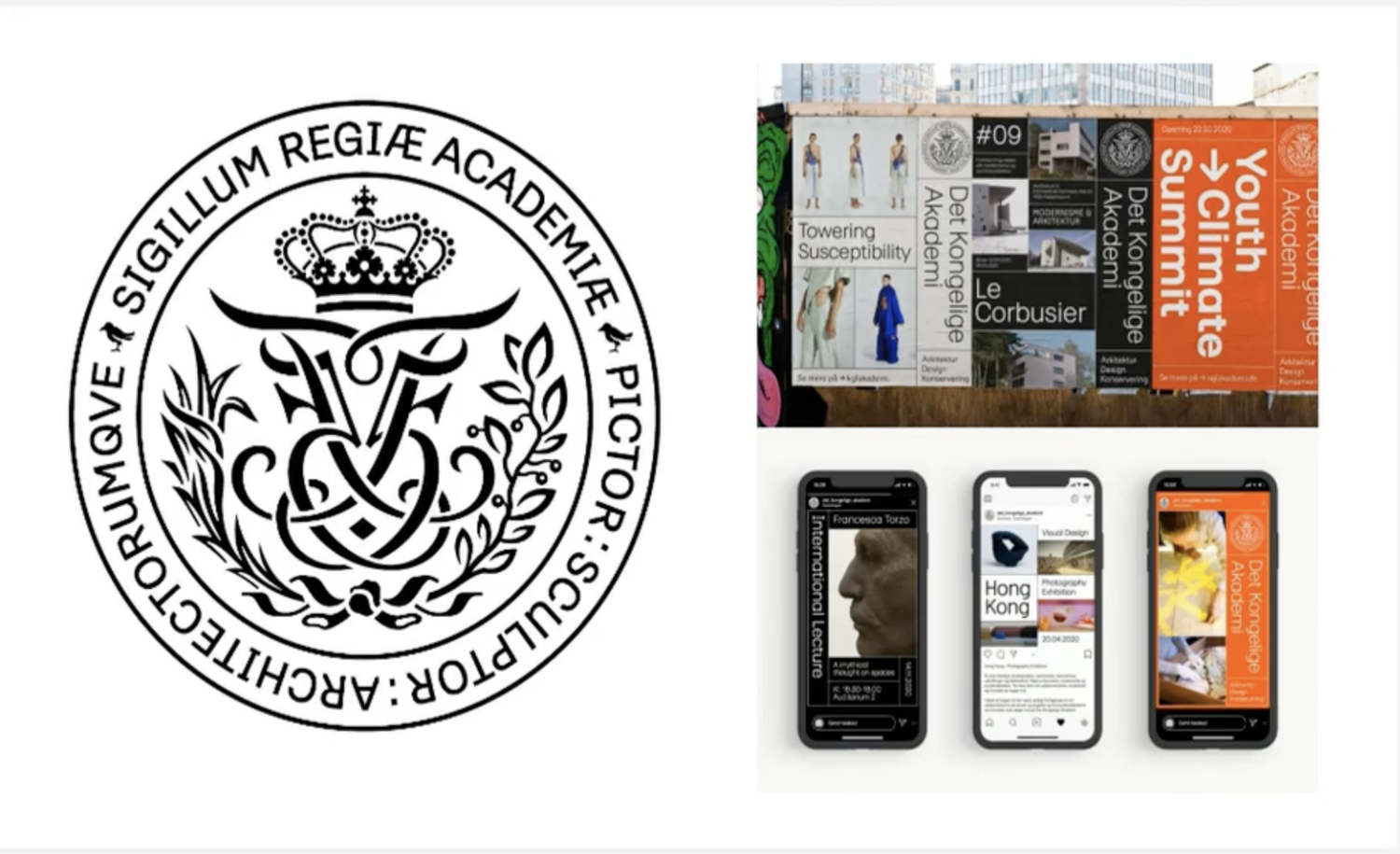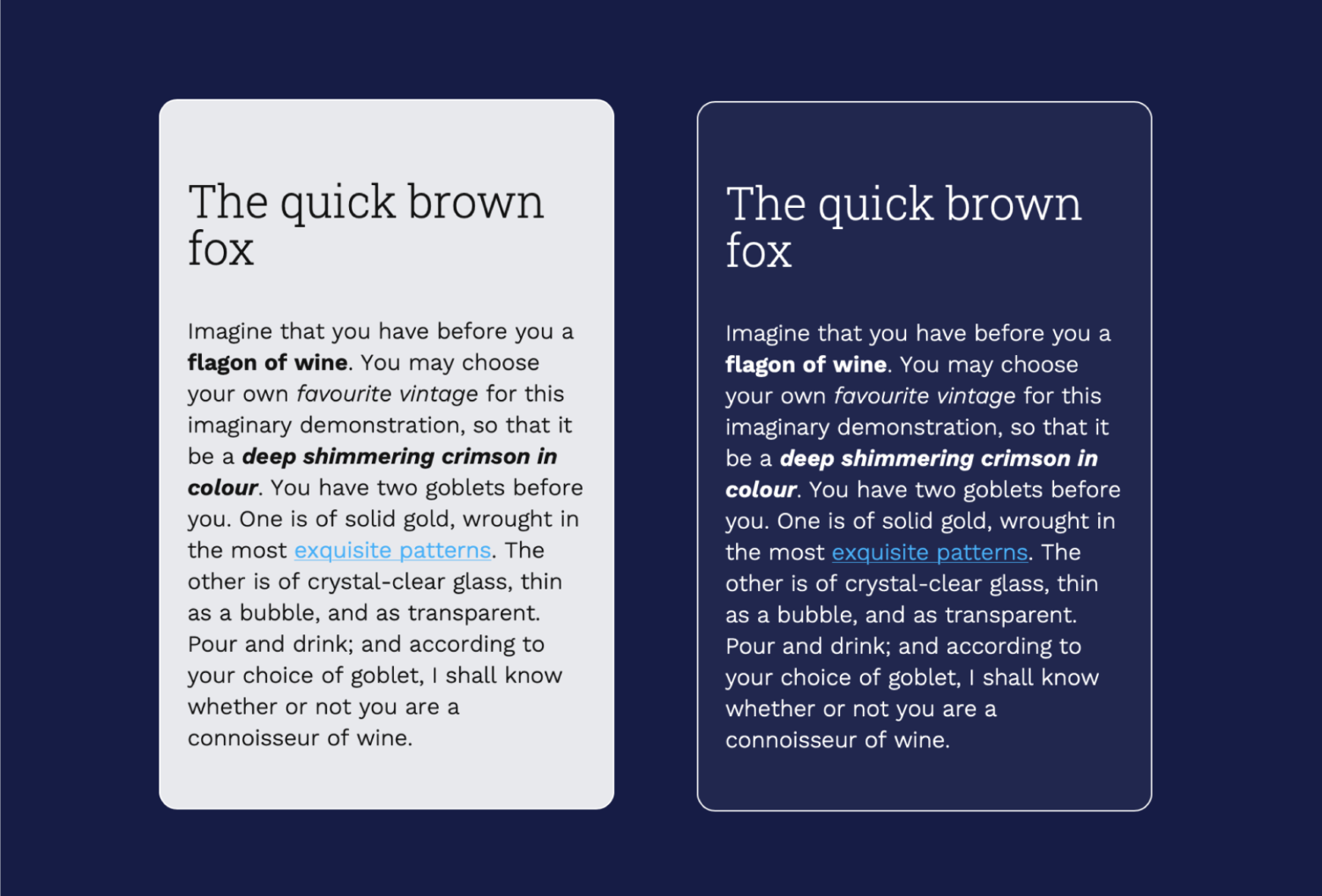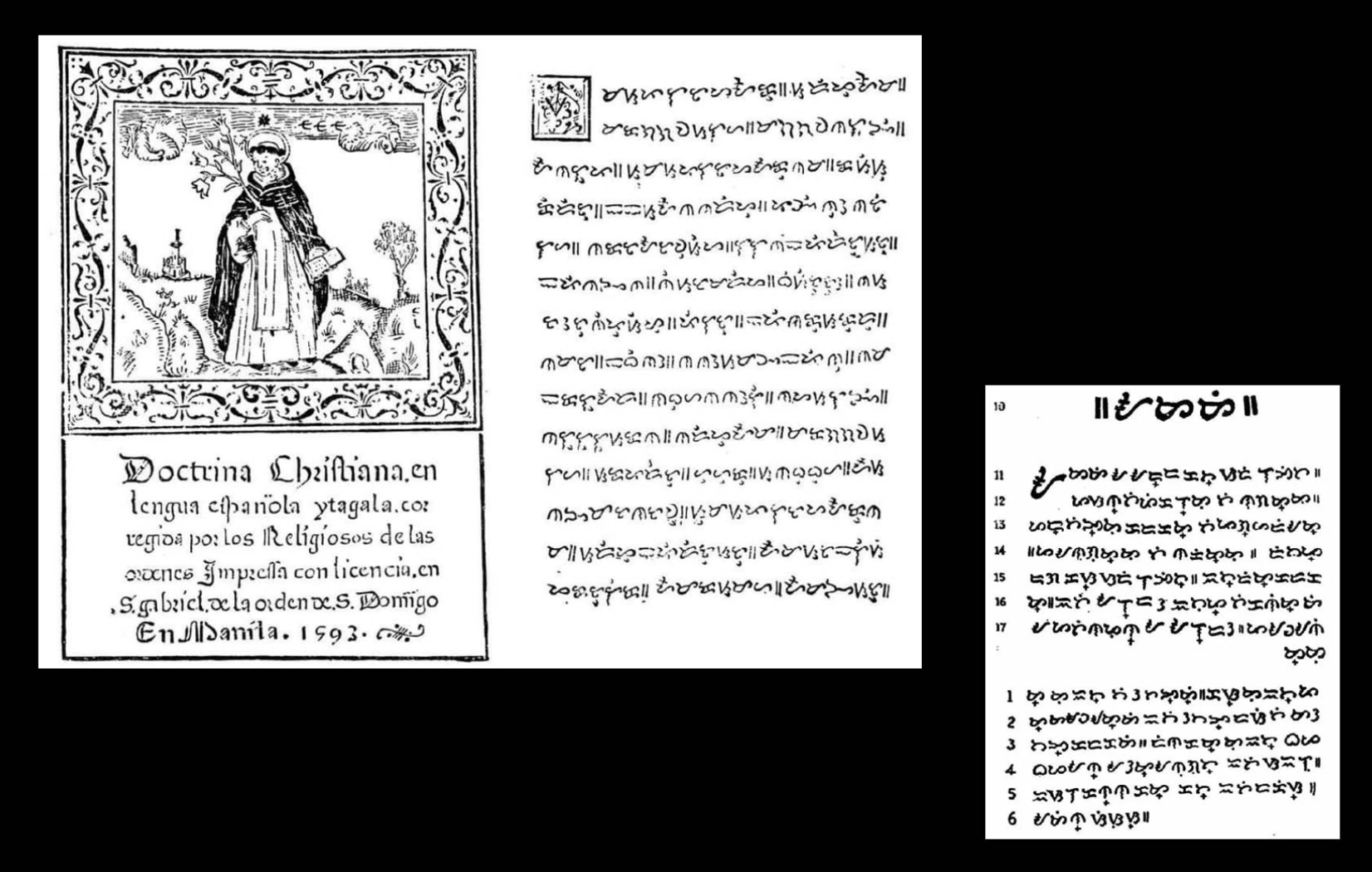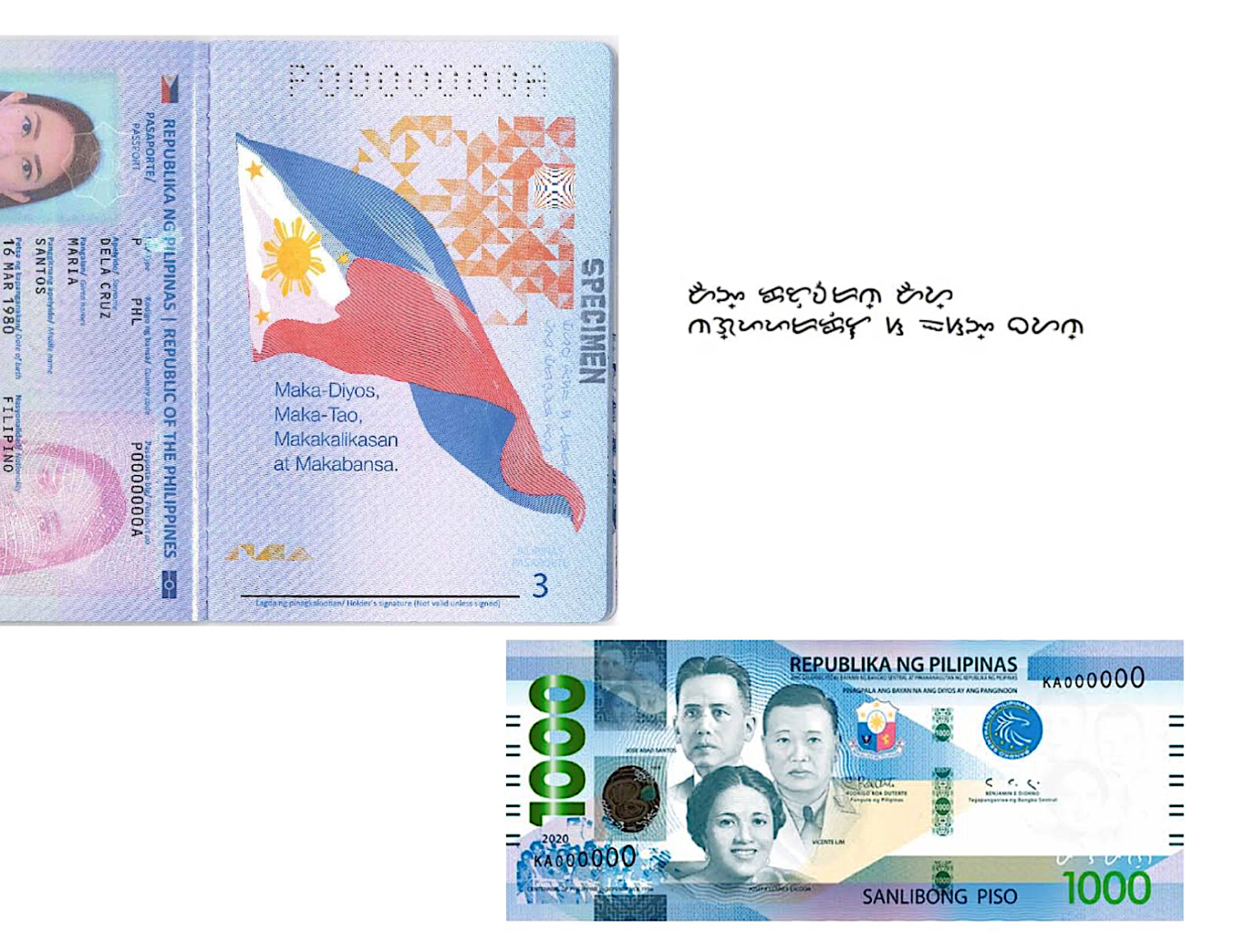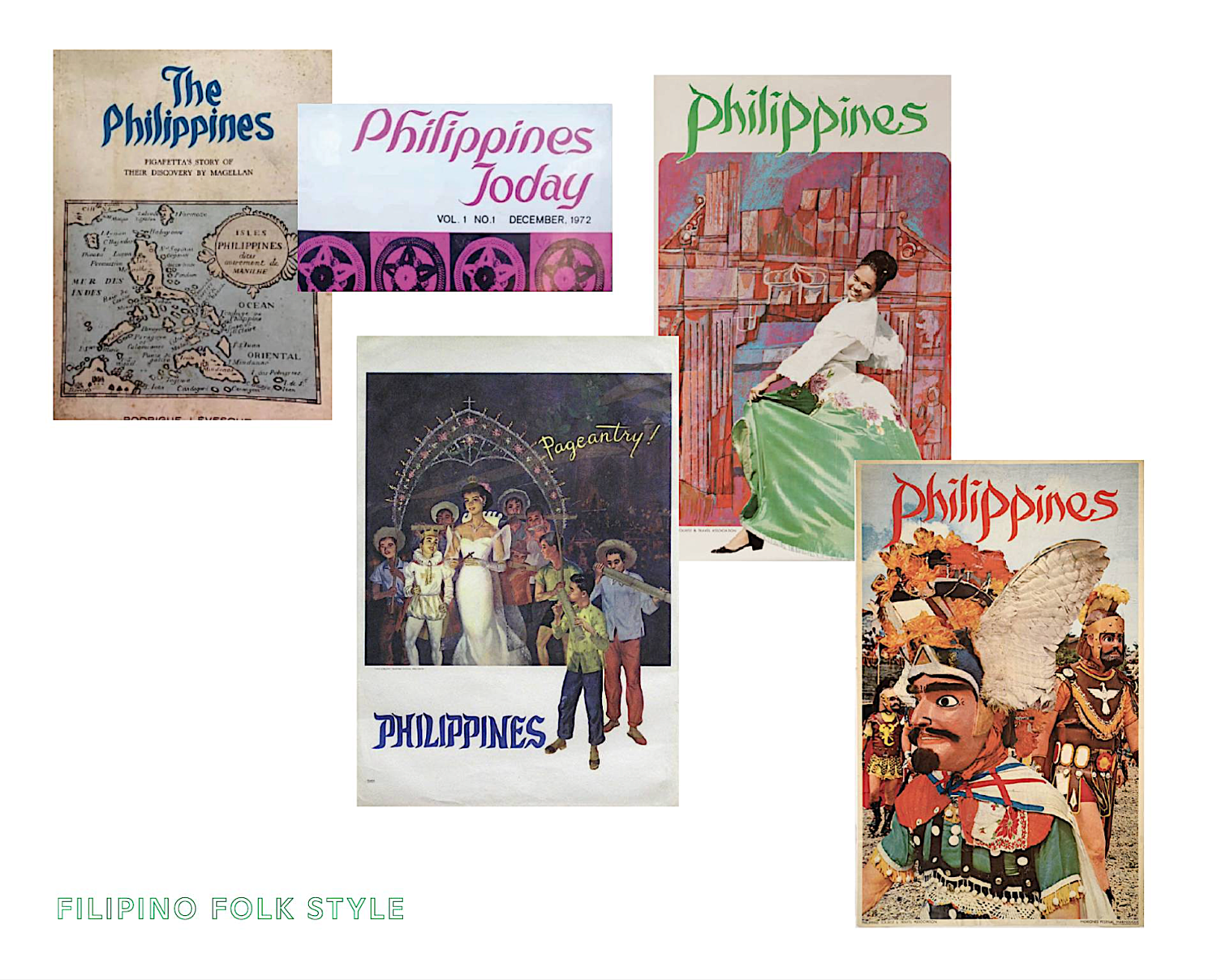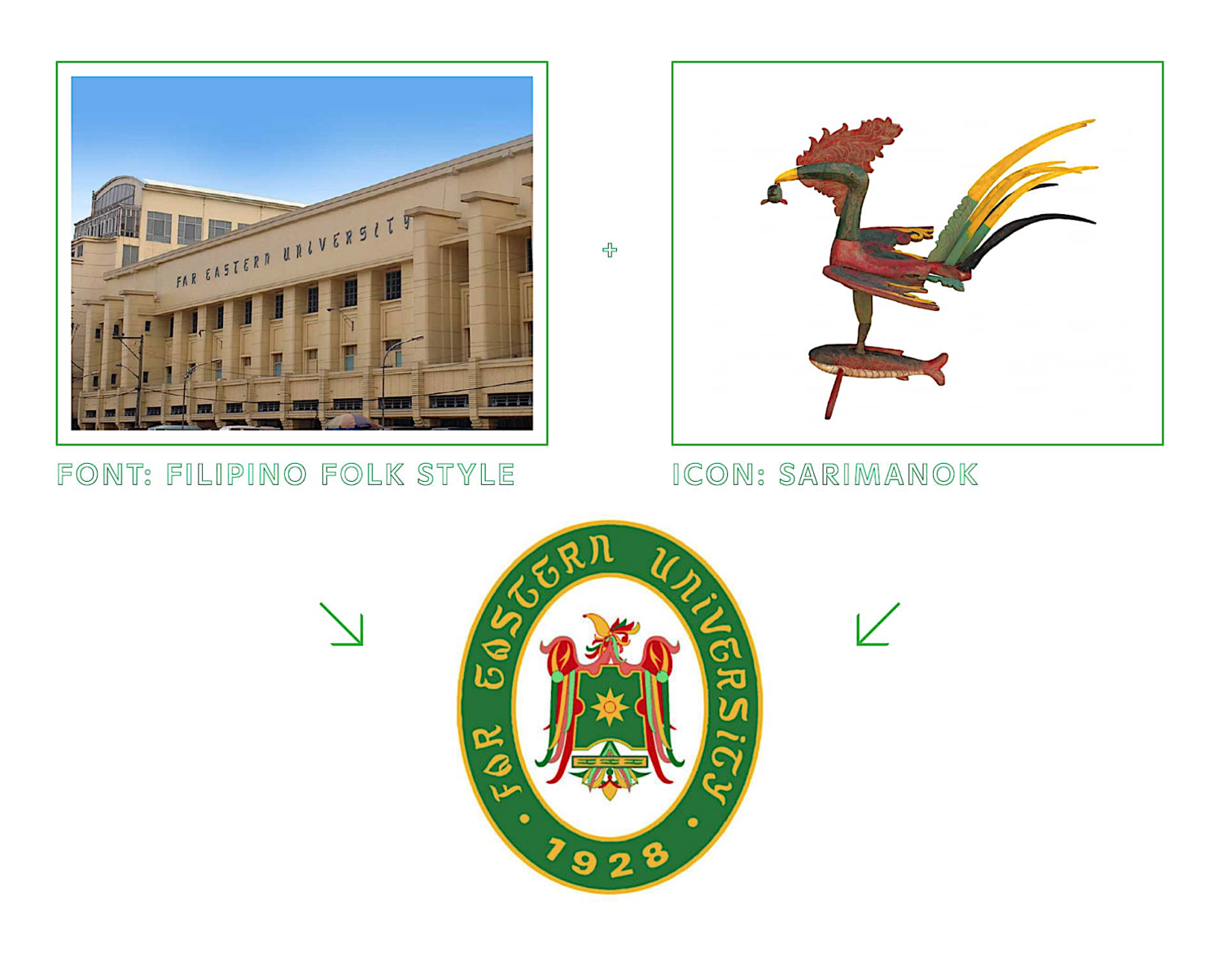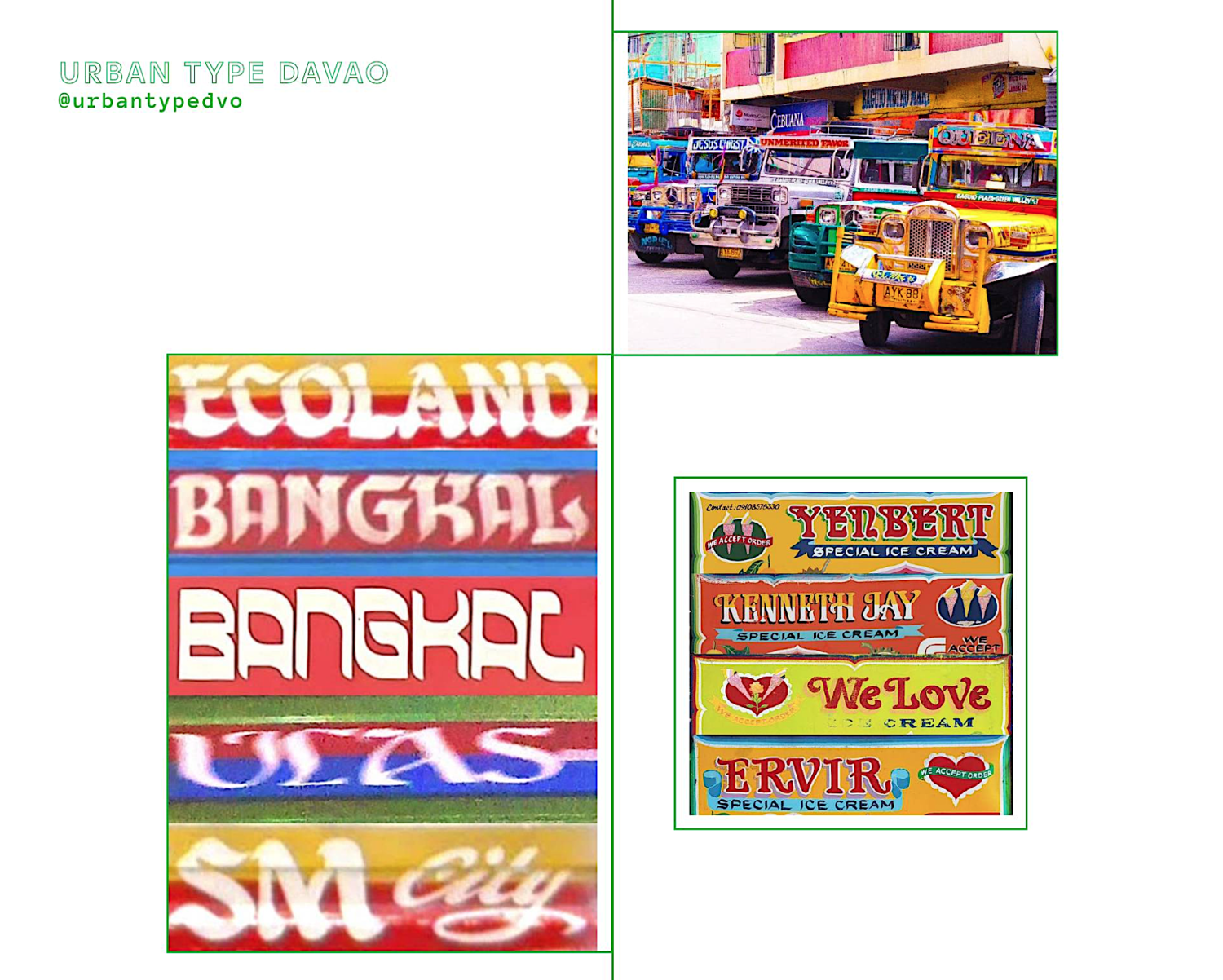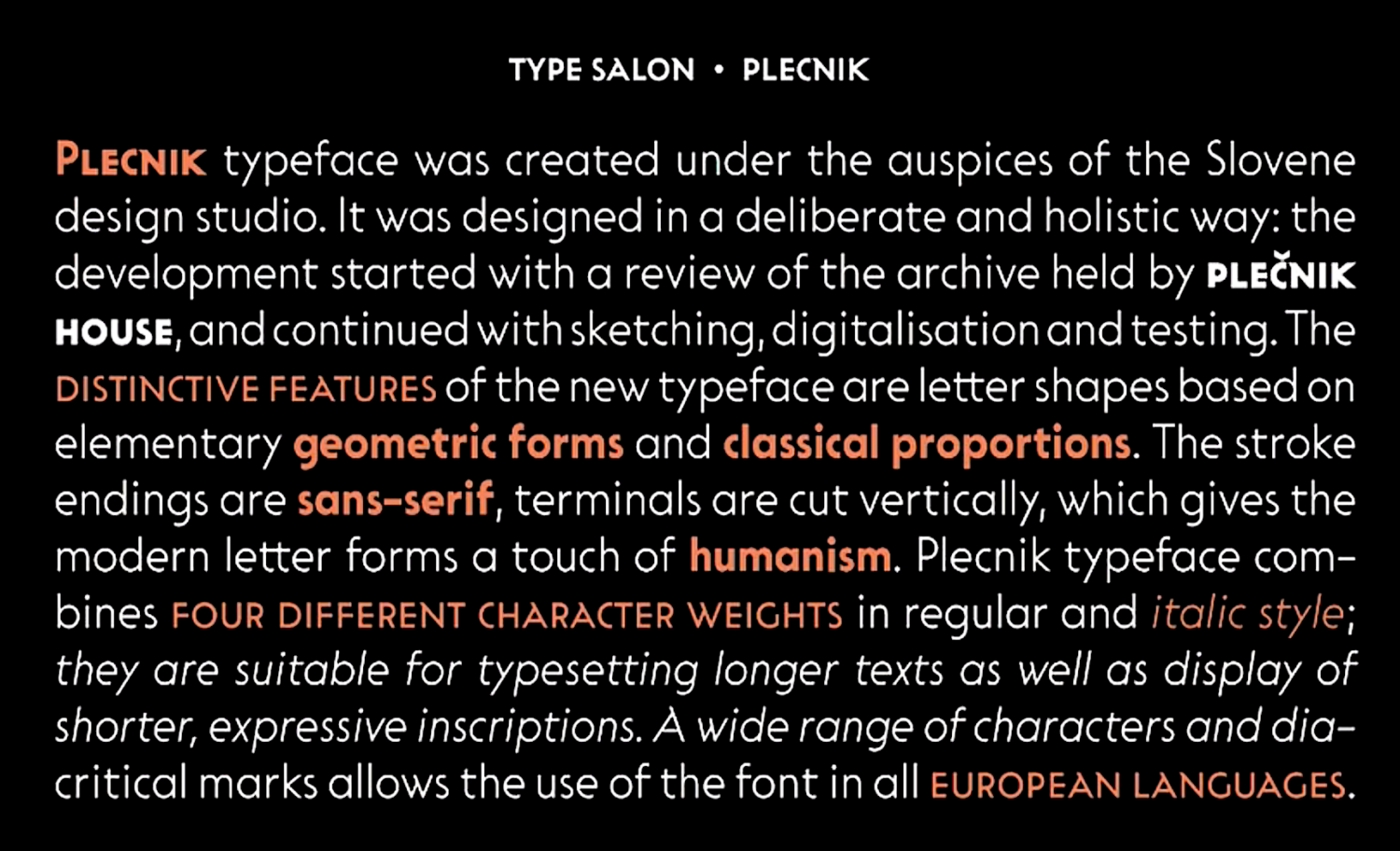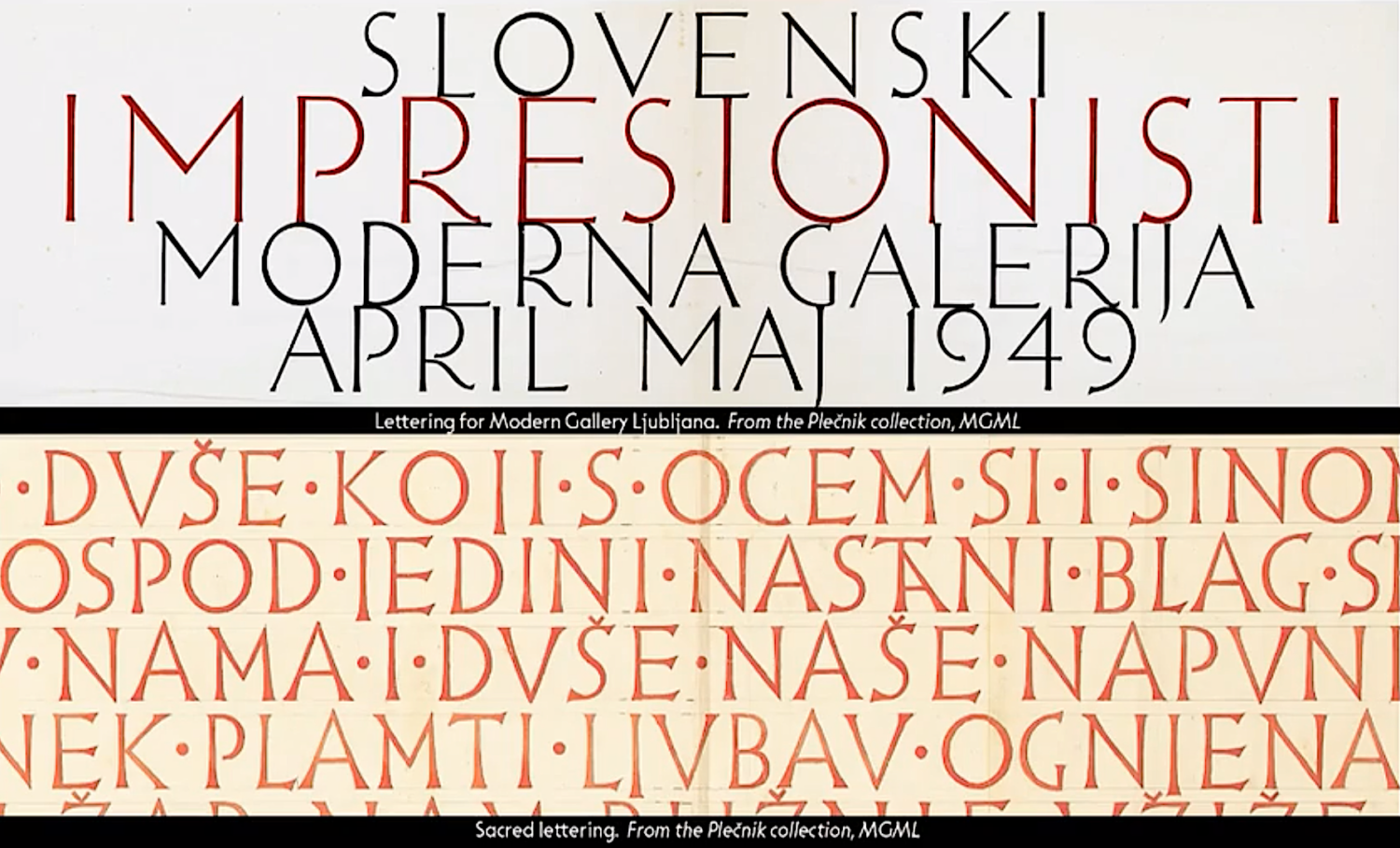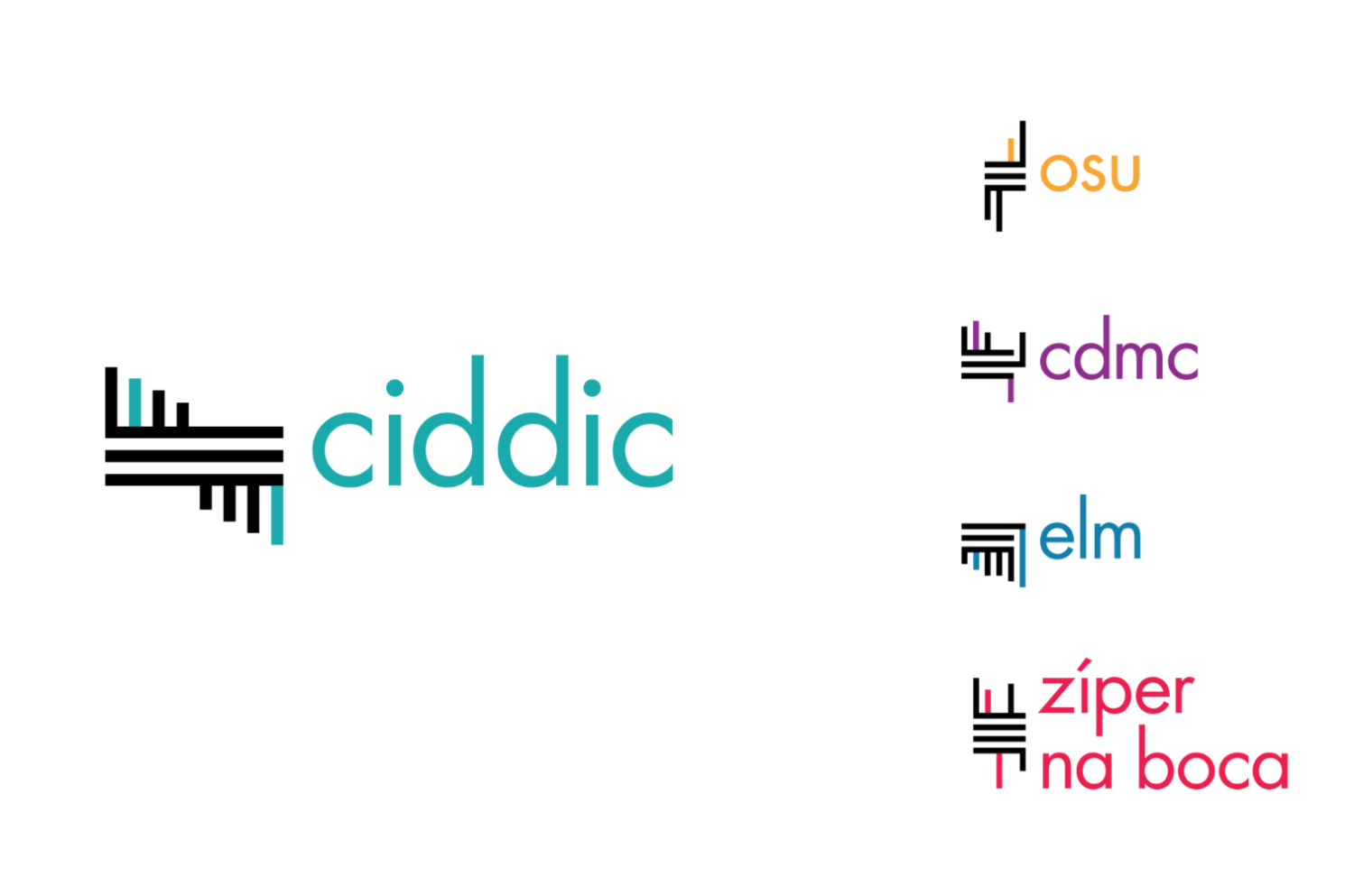
国际字体大会 ATypI · 2021 世界各地
2021 年 12 月 2 至 4 日,国际字体协会(ATypI, Association Typographique Internationale) 的年度大会在线举行。连续三天,从美国时间早八点至晚八点,全球各地文字设计师、教育者、研究者们汇聚一堂,分享这一年来的工作成果。
ATypI 演讲亮点:第一天
🎬 鲁格阿字体:复现埃及电影老海报风格
今年 ATypI 的开场演讲,由去年刚从蒙纳公司离职的日裔字体设计师大曲都市(Toshi Omagari)打头阵,为大家介绍了他新制作的一款阿拉伯文字体 Klaket。身为西文字体设计师的大曲向来擅长制作多语言文字,如蒙文、藏文等。大曲在 2016 年到访开罗,第一次访问阿拉伯世界的他恰逢《埃及电影海报艺术》一书出版,随即被这些老电影海报上的手绘文字打动,最后花了五年时间才雕琢出了这款 Klaket。
在阿文丰富的书写体类型里,易于书写的鲁格阿(Ruqʿah,رقعة)最为常见,也是阿文初学者的起点,但要做成电脑字体却极难。大曲坦言,字母基线的倾角和层叠、笔画粗度、以及字母比例,是最难调节的三个大坑。好在大曲勤奋地向蒙纳的同事以及 Instagram 上的阿文书法家们学习。不怕技术挑战的他将 Klakat 做成了首款配备字偶间距(kerning)的鲁克阿字体。普通西文的字偶对只是左右间距调整,而鲁克阿的基线是倾斜的,因此还需要随后面的字符上下移动,并相应调整间距值。为此,大曲请教了阿文专家,精选了字偶对的数量,解决了痛点。
很多阿文字体往往是为了匹配现有西文,而 Klaket 却是先有阿文,再配西文。考虑鲁克阿的倾斜基线,最后匹配上的西文粗衬线体非常厚实,大曲说「也许很适合食品包装」。整套家族也有 Regular、Offset 和 Shadow 三种风格,配合使用可以做出非常富有冲击力的立体阴影视觉效果。也许大曲的作品就是要向你证明,有时候的确「外来的和尚会念经」。
🏗 普莱奇尼克:一位建筑师的字体设计遗产
在德国、英国从事字体开发字体工作数年之后,斯洛文尼亚设计师 Alja Herlah 回到家乡首都卢布尔雅那,开始思考本国文化在字体设计中的体现。对比欧洲其他大国来说,斯洛文尼亚在铅字排印时代并没有自己的铸字厂,印刷字体大多从德意等国进口,现代字体设计受到的外来影响也非常显著。为了重新发掘视觉文化的历史源流,Herlah 开始观察城市中的历史建筑,并且逐渐聚焦于斯洛文尼亚最知名的建筑师、城市规划师约热·普莱奇尼克(Jože Plečnik,1872—1957)的作品与经历,尤其是他对本国文字视觉文化鲜为人知的贡献。
普莱奇尼克早年在维也纳求学,师从著名的新艺术风格和分离派建筑师奥托·瓦格纳(Otto Wagner),这段经历对他影响至深,使他的作品兼具古典结构的崇高感和具有人文精神的工艺细节。他前往捷克担任建筑学院教授期间还开设了字体设计课程,教学生测绘字母与数字。回到斯洛文尼亚后,他为卢布尔雅那留下了大量刻有铭文的宗教建筑、纪念碑。他的建筑手稿上到处都是精细绘制的字母,并且还在各种杂志、书籍上留下了自己的平面设计。于是 Alja Herlah 通过 Plecnik 这套字体的设计过程,综合性地展现普莱奇尼克留下的丰富视觉遗产。
在普莱奇尼克生活的年代,斯洛文尼亚先后被奥匈帝国、南斯拉夫王国等政体统治,本土的民族主义精神十分高涨,普列赤涅克的作品也体现出对家乡的热爱。这种文化溯源的渴望,在后全球化的时代重新被点燃,与 Alja Herlah 设计字体的初衷也不谋而合。
🏛 如何利用可变字体,让政府机构网页清爽好用又高效?
现居美国罗德岛州的设计师 Jason Pamental 讲述了他带领团队为州政府设计网页内容管理系统(CMS)和网站生成器的过程。Pamental 向来大力推崇可变字体技术(Variable Fonts),这次也不例外。
使用可变字体的优势主要有二:一是更精确细腻地控制排版效果,二是大大减少需要加载的字体文件数据。例如设计师为 Work Sans 指定了比常规体 400 略轻的正文字重 350,并相应降低了粗体的字重,保证小号文字显示清晰。深色模式下的正文字重则又调轻了一些,补偿在反白文字轮廓变肥、发虚的视幻觉。基于微软文字和心理学专家 Kevin Larson 的研究成果,团队还做了调节面板,用户可自行调节想要的字号、行距、字距,整个网站的文字大小层级也相应动态缩放,便于阅读障碍人士使用。为了应对各种性能不佳的设备和网速流量,Pamental 团队还基于操作系统内建字体做了大量细微调整,保证网页字体在加载前后不会导致行数行距的突兀变化而打扰交互。
项目的最终目标是能让没有设计开发背景的政府公务员也能快速建站、发布内容,Pamental 也做到了这点——因拨款削减,他现在已离开项目,但使用这套平台的州政府自疫情爆发以来已上线了包括抗疫、公卫甚至税收在内的将近 70 个新站点。新冠疫情爆发后,美国绝大部分政府机构服务都转为线上,而使用政府服务的人既有手持新款 iPad 的都市白领,有还用着老掉牙的 Windows XP 和 IE 浏览器的大型机构,也有只买得起廉价三星手机、精打细算使用流量的单亲妈妈。从这个角度看,Pamental 做的也许不仅是可达性设计(accessible design),而是通用设计(universal design)——以最灵活的方式、最低廉的成本,惠及最多的人。
📂 微软 Office 套件推出的字体新功能,对谁最有用?
作为银质赞助商,微软每次都不会缺席 ATypI 年会,而今年 Si Daniels 就给大家介绍了 Office 在字体排印方面的功能更新。虽然大家都很关心微软究竟会从五个备选字体中挑选哪一款作为 Office 的下一代默认字体(参见《字谈字畅》播客 153 期的播报评论),但他们表示还要纠结到明年。今年他们推出的大戏则是「Office 云字体」,体现了其坚持走云战略的决心。
在明年将会公布的新功能里,首先是和用户打交道最多的「字体选择器」。微软终于下定决心改善冗长的字体菜单,改善了分区,各个分区可以折叠,二级菜单也有所改进。画面右侧新增的「信息面板」则会提供约 250 字的信息,其中八成内容是字体的使用建议,而剩下二成则是字体的详细信息,相信能为字体一头雾水的用户有所帮助。而在后台悄悄导入的「兼容字体」功能,虽然在字体菜单里只是一个小小的提示,但实质上则是在后台自动为用户下载本地没有的一些开源字体,这些都实实在在地节省了用户的宝贵时间。当然,软件还自动挑选当前文种的「十佳字体」,用大头针定位在字体下拉列表里,但用户到底会不会对这种自作主张的推荐买单,就要靠实践证明了。
本次发布的另一大功能则是「企业组织字体」,允许管理员将企业的定制字体上传到 SharePoint 服务器,仅供企业内部用户使用。这个方案既不需要用户嵌入、也无需安装,企业可以更快捷地部署定制字体,还绕过了知识产权问题。
微软在 ATypI 大会上公布此消息,其实是希望字体创作社区要充分考虑字体授权范围,对这类字体的使用放宽处理。微软毕竟是还是那个微软,对自己的收益渠道抓得很精准,服务于企业用户才是它维持市场份额的不二策略。
ATypI 演讲亮点:第二天
🇵🇭 菲律宾字体社区的活动:反殖民与现代化之间的挣扎
「菲律宾至少有 120 多种语言,大家知道吗?」作为可能是第一位登上 ATypI 讲坛的菲律宾字体设计师,Clara Cayosa 在演讲前半段特意花了大量时间为大家介绍这个既熟悉又陌生的国度,以及她带领的字体社区 Tipong Pilipino 进行的各种活动。
经过西班牙和美国的殖民,规范化的他加禄语已经被改名为菲律宾语,与英语一并成为官方语言,但这也一直是菲律宾人的心结:「我们没有吴哥窟,没有泰姬陵,那么我们是谁?」现今的菲律宾设计师们甚至从历史的故纸堆了翻出废弃的本土文字拜拜因字母(Baybayin),它们与拉丁字母结合形成了八十年代菲律宾字体设计的一大风格。这种看似笔画怪异、充满异域风情的拉丁字母,却歪打正着地成为菲律宾民族的象征被广泛使用。
然而高手依旧在民间,各种野生的手写招牌和笔刷文字依旧是菲律宾字体风景的重要组成部分。Cayosa 带领设计师团队,不仅拜访了多位手写招牌师傅,还拜访了伊罗戈斯地区能在传统织物 hinabi 上编织字母的一位老妇,她可是唯一一位掌握此工艺、并能熟练控制字距编织成型的女匠人。这些眼花缭乱、个性张扬的民间字体高手们的技艺,比当年那些为反殖民、国家意识而生造的空洞风格要显得丰满得多。
🇪🇨 创造原住民语文字:长路漫漫
与我们往年报道过的非洲文字的状况相似,拉丁美洲的许多原住民语言从未发展出属于自己的文字书写系统,例如厄瓜多尔的 14 种原住民语,目前都借用拉丁字母来书写,这也是他们在 16–19 世纪一直是西班牙殖民地的结果。在如今复兴本土文字的大潮下,像 Juan Casco 这样的本地设计师和艺术家也开始通过「生造文字系统」的尝试来表达文化身份。但这一过程绝非易事。
现代新创的文字系统往往是表音文字,但也要根据语言特征,在全音素文字(如拉丁字母、韩字)、元音附标文字(如藏文、天城文)、辅音音素文字(如阿拉伯文)等中选择。Casco 首先研究了这些现存文字的构成逻辑,并与语言学家、人类学家合作,设计了一套元音附标文字 SilAm,希望用来书写多种美洲本土语言。
虽然这套设计看上去清晰友好,但如同任何新创的文字系统一样,它真正的成功不在于设计而在于实际应用。为此,需要普及读写教育、研发输入法、为它争取 Unicode 编码字段、开发数字字体等等,SilAm 文字系统还有很长的路要走。Casco 也提倡用彩色字体的格式来保留玛雅文字、或用颜色代表不同意义的印加 Tokapus 文字,但不得不说这些都是千里中的跬步。
🇦🇪 阿文视觉文献宝库:现代字体实验的练习场
Nada Abdallah 是阿联酋的设计师和策展人,也是阿联酋沙迦大学艺术学院的助理教授。她的教学项目和学生作品,让观众可以一窥目前阿拉伯文设计学生们(绝大部分都是女性)如何通过文字设计实验重新发现自己的视觉文化历史。
学生们在项目中研究了整个阿拉伯地区的视觉文献,在 1960–80 年代的各种手绘设计中——如海报、书籍、杂志、唱片等——挑选灵感,将风格化的书法设计转换成数字字体。尽管这种风格化模仿的研究深度和学术水平有待评议,学生作品的成熟度也参差不齐,但她们所参考的视觉文献之丰富,让人不禁感叹阿拉伯文的书写与设计的无限变化的表现力。
最后 Abdallah 还组织学生作品参加了今年庆祝阿联酋建国的纪念活动,用这些字体写出了部分国歌歌词并组成国旗式样,学生们在国歌声中为祖国献礼的景象不由令人感到十分熟悉。
中文相关演讲汇总
来自大中华地区的演讲者们同样为大会献上了精彩内容,从史料研究、设计实验到公共文化,主题丰富而多元。我们也在《字谈字畅》播客中专门对中文演讲者进行了访谈。
- 《西夏字体研究与 Noto 西夏宋体再设计》,刘钊(中央美术学院副教授)、杨翕丞(英国雷丁大学字体设计硕士在读
、宋霈霖(中央美术学院本科生) - 《聚珍仿宋体的开发及其传播》,孙明远(澳门理工学院艺术高等学校副教授)
- 《业余的观察和记录》,姜庆共(城市居民、设计爱好者、字体使用者)
- 《童叶庚与〈益智图千字文〉》,周晨(南京艺术大学硕士研究生导师、凤凰教育出版社编审、艺术出版中心主任)
- 《一定要方块吗?跨文化中文排版中的实际问题》,陈秋惠(台北平面设计师,way2creative 设计工作室主理,Circle 杂志主编、伯明翰时尚创意学院讲师》
- 《字体传递品牌声音》,吴昊轩(方正字库产品经理)